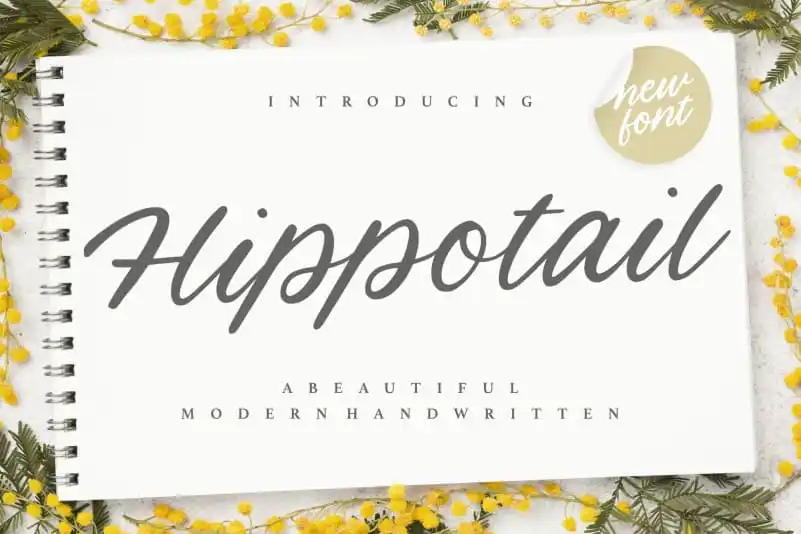
Hippotail Handwritten Font – Download Grátis
A fonte “Hippotail Handwritten” é perfeita para criar designs envolventes que capturam a essência do design de escrita cursiva em sua melhor forma. Essa fonte tem uma magia única, capaz de dar um toque autêntico e criativo aos seus projetos digitais. Suas linhas suaves e detalhes delicados se adaptam perfeitamente para produtos de embalagem, design de marca, revistas, mídia social, ou até mesmo para adicionar uma atmosfera única a mensagens em fundo. Essa fonte é um must-have para quem procura trazer personalidade e vida aos seus projetos digitais, seja eles de comunicação corporativa ou expressões artísticas. Seja você criando um design elegante para sua marca ou adicionando uma pitada especial a sua newsletter, essa fonte será uma escolha inspiradora e versátil.